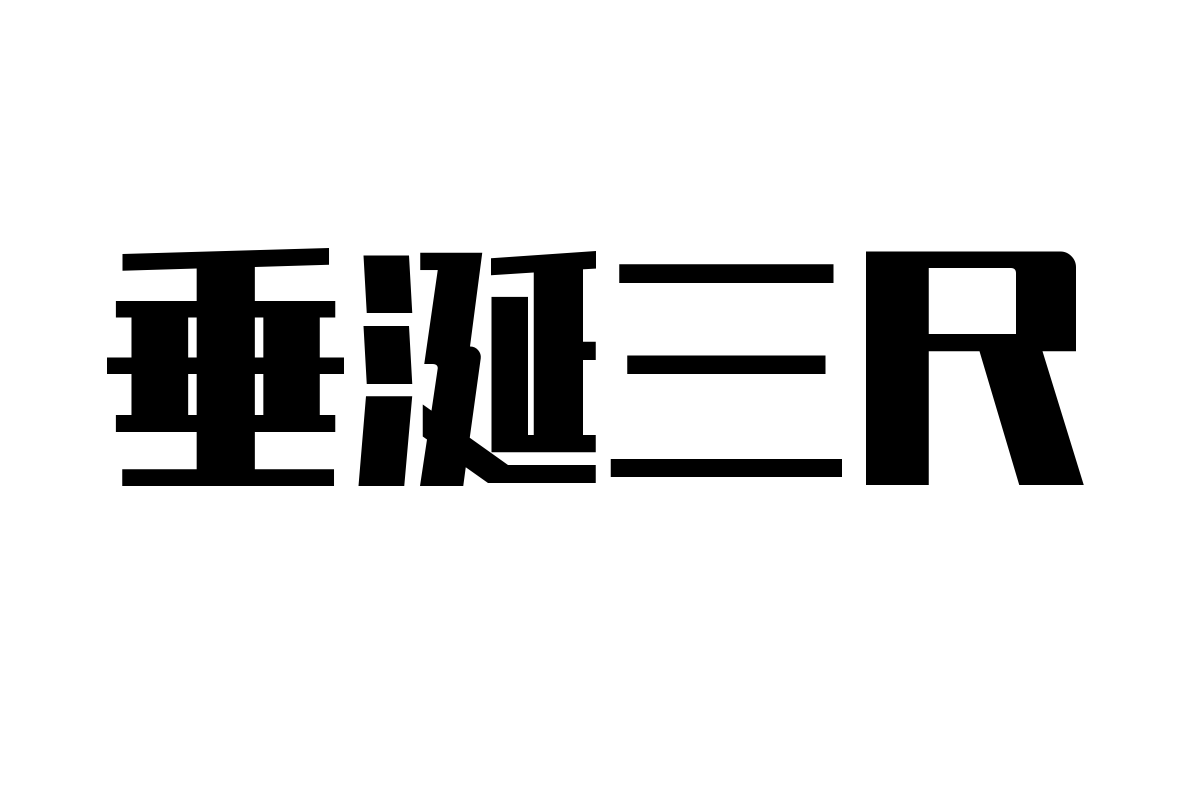
锐字潮牌真言超粗字体是一款非常独特和引人注目的字体。它的笔画粗细不一,给人一种强烈的视觉冲击感。这种字体的设计灵感来源于现代街头文化和涂鸦艺术,因此它充满了活力和个性。
锐字潮牌真言超粗字体的特点是:笔画粗细不一,形状各异,给人一种强烈的视觉冲击感。它的线条流畅,富有动感,能够很好地表达出文字所要传达的情感和态度。同时,这种字体也具有很强的可读性,因为它的笔画清晰,易于辨认。
锐字潮牌真言超粗字体适用于各种场合,如广告、海报、设计作品等。它能够吸引人们的眼球,让人过目难忘。无论是用于品牌宣传还是个人创作,锐字潮牌真言超粗字体都能为你的作品增色不少。
总的来说,锐字潮牌真言超粗字体是一款非常独特和引人注目的字体,它的独特性和可读性使它在众多字体中脱颖而出。无论你是设计师还是普通用户,都可以尝试使用这款字体来表达自己的创意和想法。